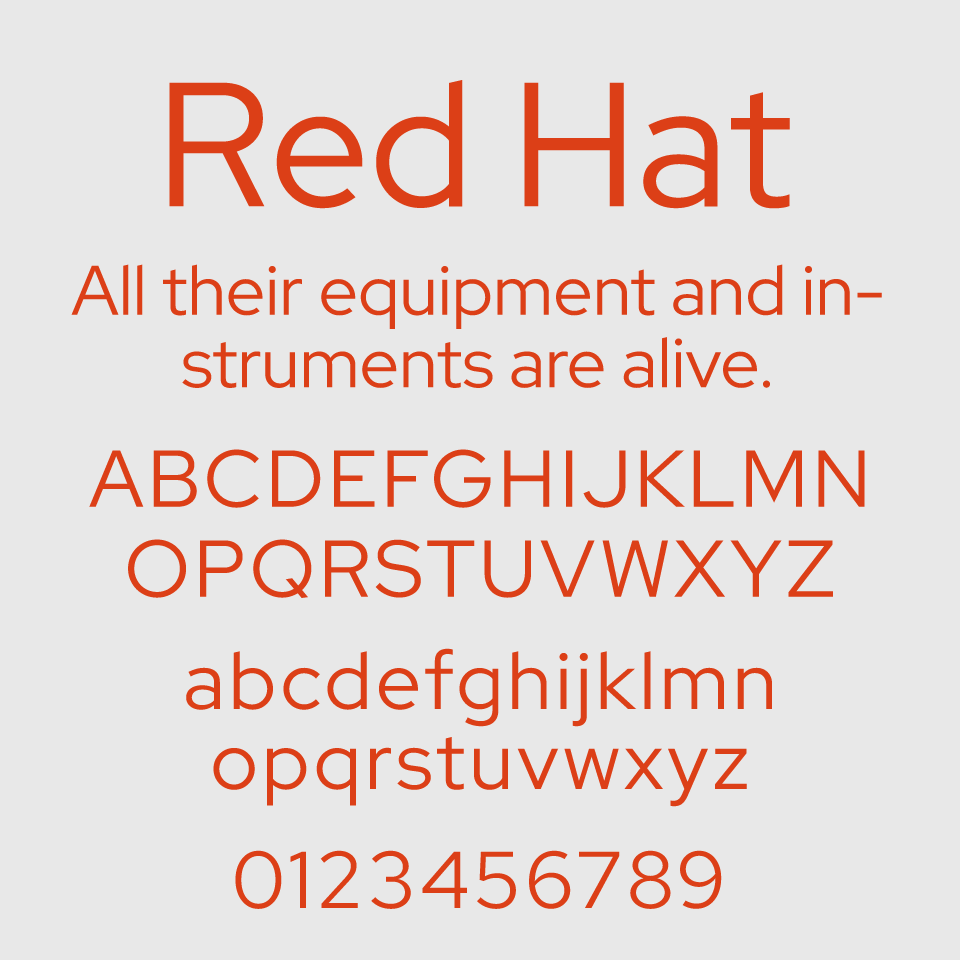
Red Hatは、端正さと柔らかさを両立した現代的なサンセリフ体です。
可読性が高く、整った字面が印象的で、落ち着いた印象を持ちながらも堅苦しさはありません。デジタル環境でも非常に読みやすく、UIデザインや長文表示にも適したバランスの良い設計です。
中庸なデザインながら、角のとれたフォルムにどこか親しみがあり、堅実さとやわらかさが共存しています。信頼感を求めるコーポレートツールや教育系コンテンツなどにも自然に馴染む、万能なフォントです。